iOS7のフォントについてiOS7beta5
iOS7フォントの特徴
フラットデザインばかり取り沙汰されているiOS7ですが、フォントもデザインの一部として多くの変更があります。
デザインに適したフォントの追加は珍しいことではありません。
そして、iOS7のフォントの特徴は、やはり「細字」ではないでしょうか。
iOS6の時、多くのフォントに「Condensed Light」やら「UltraLight」やら追加されたのが妙に引っかかっていたのですが、今思うと、iOS7への布石だったのかもしれませんね。
どんなフォントがあるかは、この後の一覧で紹介しますが、私が特にイチオシしたいフォントがヒラギノ角ゴシックです。
ヒラギノ角ゴシック
あれっ? ・・・と思った方は大正解ですね。
iPhoneで表示される日本語と言えばヒラギノ角ゴシックなので、今さら何を言い出すのか?という感じが満載かと思います。
しかも、イチオシって・・・
実は、iOS7フォントの特徴として挙げられた「細字」が、ヒラギノ角ゴシックにも追加されているのです。
これまでのiOSでは、W3とW6の2種類の大きさのフォントが用意されていましたが、今回のiOS7用にW1とW2が追加され、全部でW1・W2・W3・W6の4種類になりました。
さらに、面倒なことかどうかはまだ分かりませんが、このヒラギノ角ゴシックが、OTFからTTCに変更されました。
ちなみに、ヒラギノ明朝はOTFのまま残っています。
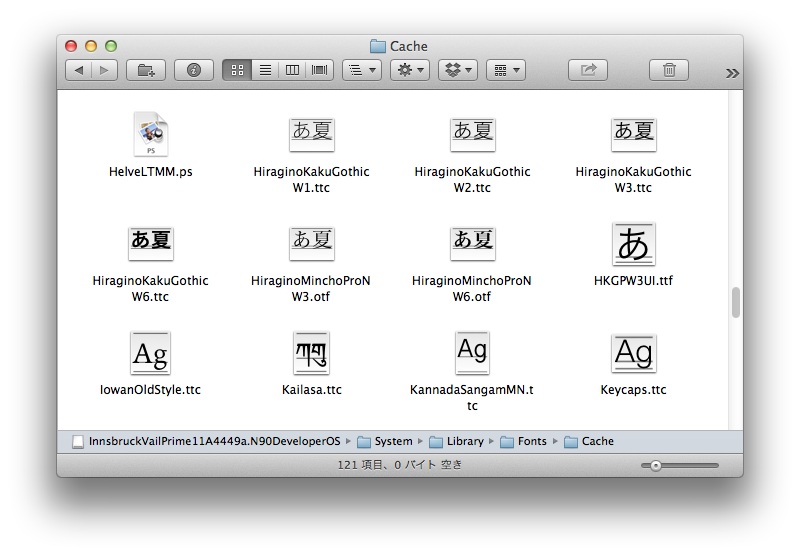
それぞれの太さの違いは、以下の通りです。
W1です。
一番細いフォントでございます。
W2です。
W1より太くなっていることが分かります。
W3です。
かなり太く見えますが、これでも従来の細字用です。
W6です。
めちゃくちゃ太く見えますが、よく目にしているホーム画面のアイコンラベルはこの太さです。
CGFontCacheについて
せっかくなので、CGFontCacheについて軽く触れておきます。
CGFontCacheは、以下のように5つあります。
ここで、CGFontCache@2x.plistを開いてみます。
Namesだけ見ても、iOS6.1.2では429itemsだったので、150程度増えています。
名前の定義は、無駄な定義をしていてもカウントされるので、増えたなぁ〜という感じで構いません。
TraitMappingsの方は、iOS6.1.2では80itemsだったので、こちらは20程度増えています。
マッピングはフォントファミリーの割り当てなので、20も増えるということは、個人的にとてもウキウキします。
Versionの7.0.8は、ベータ版だからかなぁ?という感じで、あまり気にしていません。
では、Namesを見てみましょう。
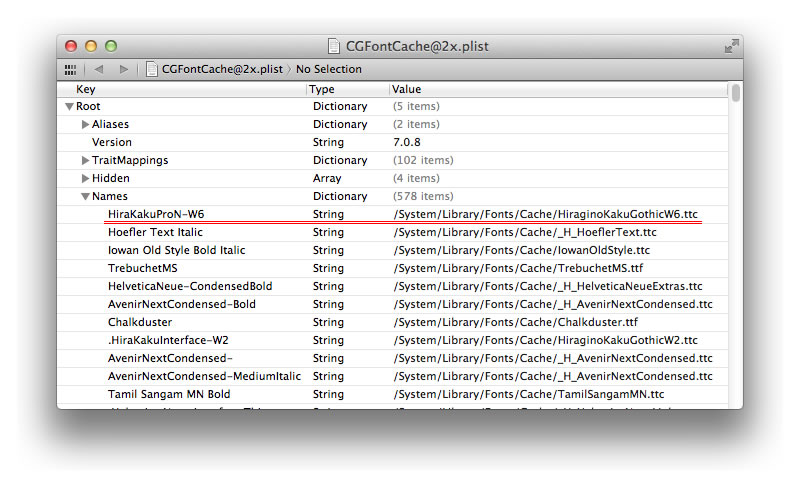
赤線を引いておきましたが、ヒラギノ角ゴシックの一番太いフォントが、"HiraKakuProN-W6"と定義されています。
当たり前ですが、TTCのフォントを指定していますね。
これまでは、ここがOTFでしたからねぇ・・・
次に、TraitMappingsを見てみましょう。
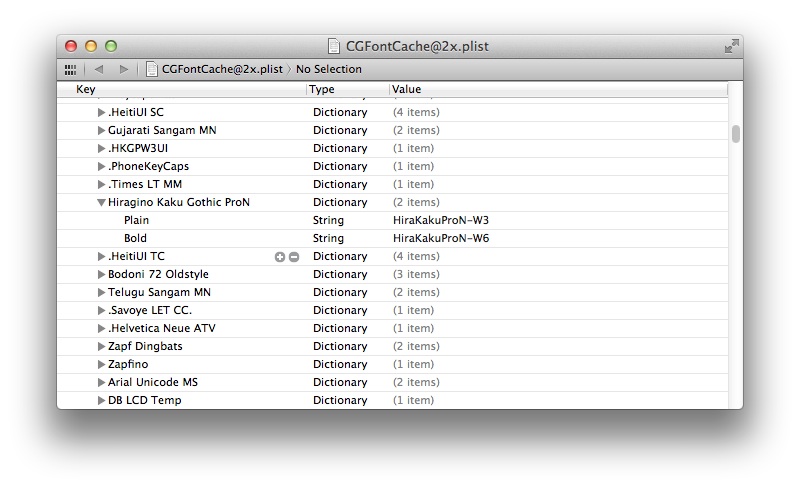
ヒラギノ角ゴシックのフォントファミリー部分と思われる「Hiragino Kaku Gothic ProN」を開いてみたのですが、これまでのようにW3とW6しかありませんでした。
そこで、もう一度Namesを見てみましょう。
画像は先ほどと同じ画像ですが、注目する部分が違います。
こちらも赤線を引いておいたのですが、W2の定義名が、".HiraKakuInterface-W2"となっております。
今度は、この定義名を意識して探してみると・・・ありました!!
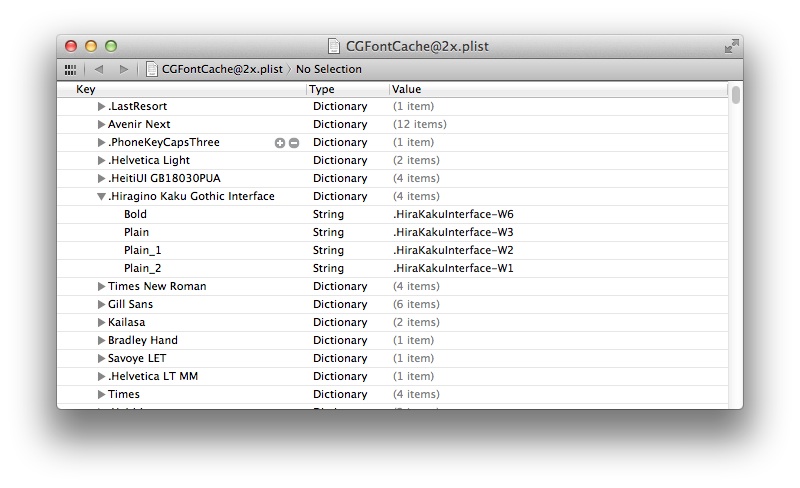
".Hiragino Kaku Gothic Interface"のところに全部ありました。
なぜ、"Interface"なのだろう???と考えてみました。
"Interface"という文字もそうなのですが、他にこの"Interface"が付いているのが、あの"Helvetica Neue"だったのです。
このことから、 "Interface"の付いたものがシステムフォントとして使われているのでしょうね。
さきほどの、W3とW6だけのものは、iOS7未対応アプリのフォント指定用なのではないでしょうか。
フォント一覧
ヒラギノ角ゴシックもHelvetica Neueも、"Interface"のフォントが表示されていないのです・・・